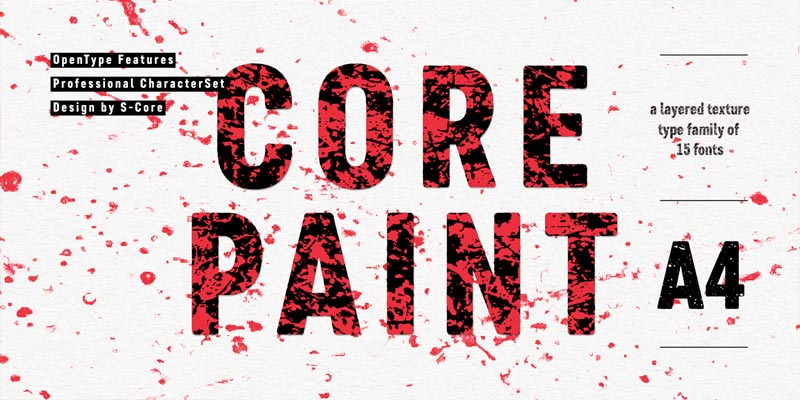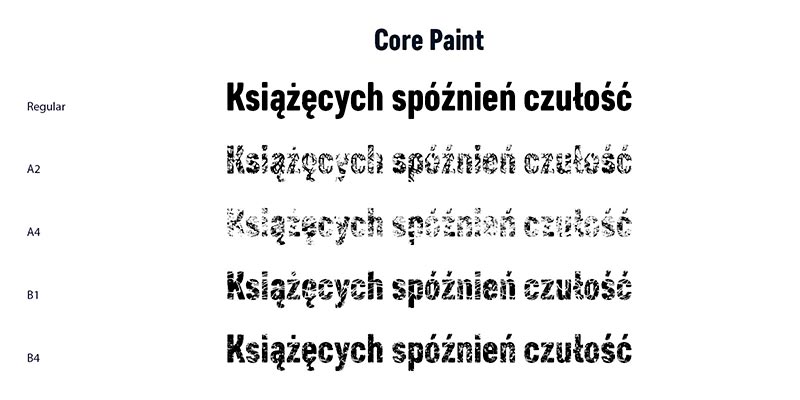
Font Core Paint
Do naszego studia trafił teksturowany font Core Paint. Zestaw składa się z 15 odmian, które można łączyć ze sobą, uzyskując szeroką gamę naturalnie wyglądających efektów rozlanej farby.